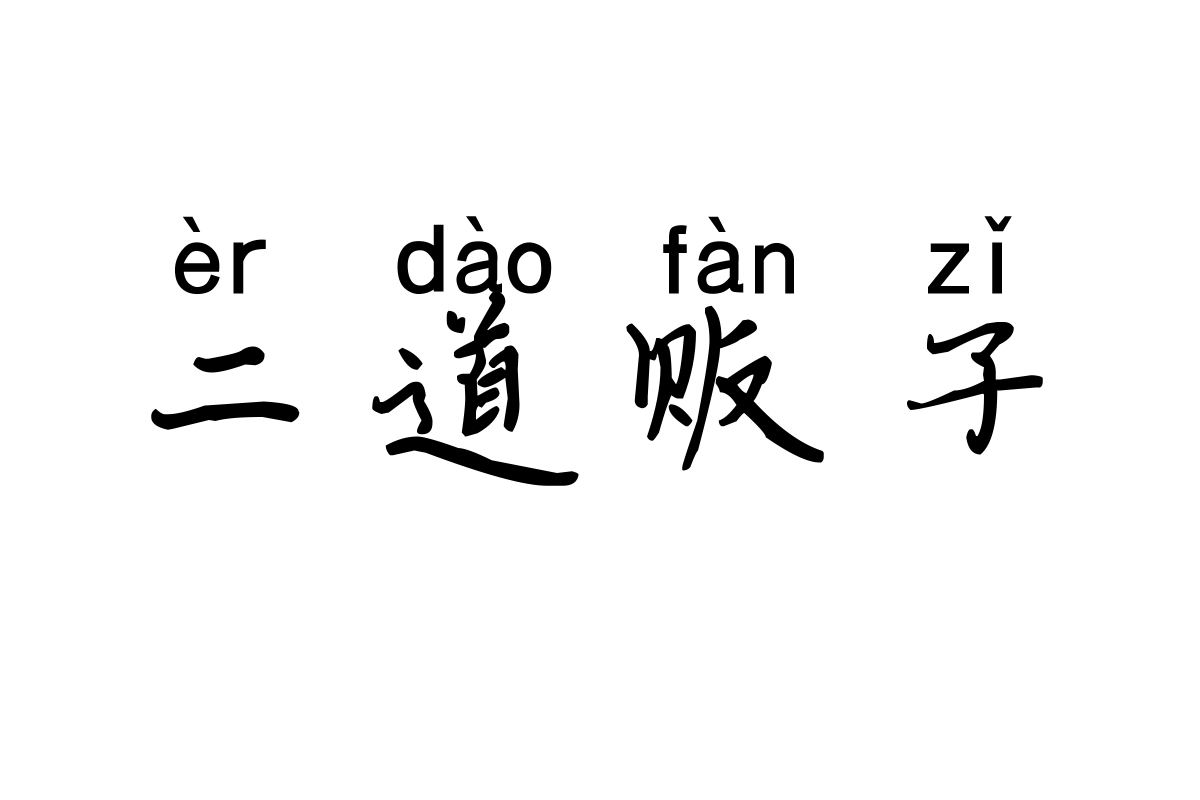
米开簪花小楷拼音体是一种具有独特风格的中文字体。它的设计灵感来源于中国的传统书法艺术,特别是米开簪花这种古代的书写工具。该字体采用了小楷的形式,笔画精细,结构严谨。
米开簪花小楷拼音体的特点如下:
1. 笔画精细:该字体的笔画线条流畅,细节处理得当,给人一种精致的感觉。
2. 结构严谨:字体的结构紧凑,每个字的笔画都排列整齐,没有冗余的部分。
3. 风格独特:米开簪花小楷拼音体的设计风格独特,既有传统书法的韵味,又不失现代感。
4. 适用场景广泛:该字体适用于各种需要展示传统文化和艺术氛围的场合,如广告、海报、书籍等。
总之,米开簪花小楷拼音体是一种具有独特风格和实用性的中文字体,适合用于各种需要展示传统文化和艺术氛围的场合。